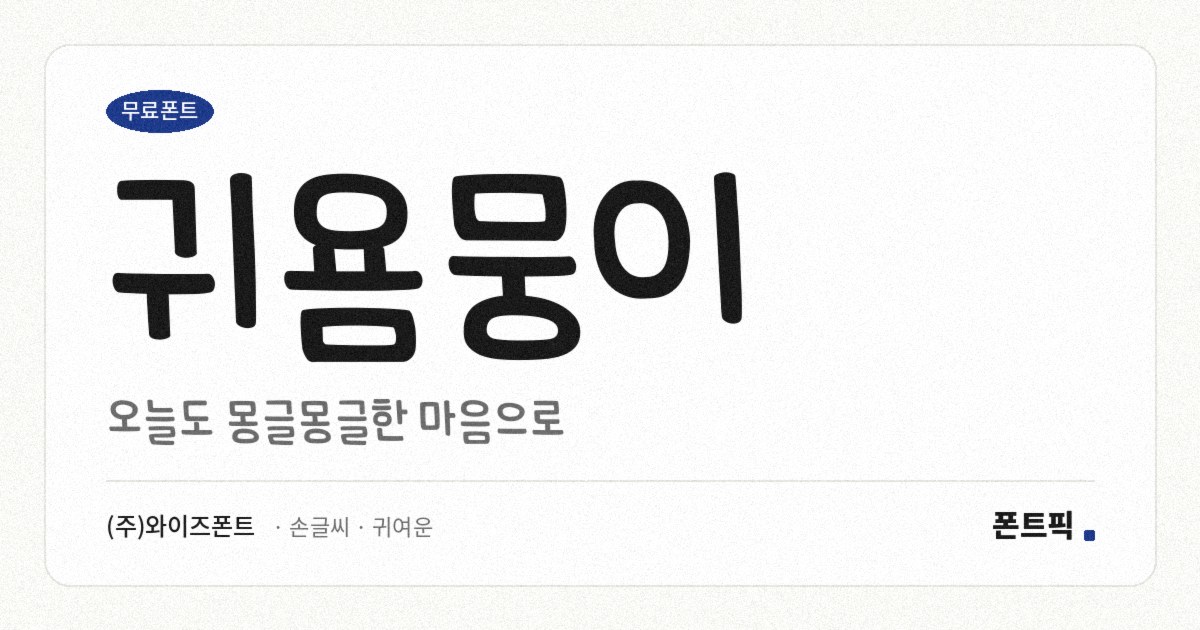
귀욤뭉이
TDTDCuteDoggy
- 분류손글씨 · 귀여운
TDTDCuteDoggy
이름처럼 둥글고 통통한 서체입니다. 획 끝을 굴리고 속을 채워 인상이 부드럽습니다.
파일에서 재어 보면 받침이 붙을 때 글자가 0.14em쯤 내려가 손글씨의 흔들림이 조금 남아 있지만, 같은 회사의 별헤는밤이나 푸들처럼 크게 오르내리지는 않습니다. 손글씨와 고딕의 중간쯤에 있는 셈입니다. 낱자는 정사각형에 가깝고 세로획이 가로획보다 3할쯤 굵습니다.
장식이 들어가지 않아 쓰임이 넓습니다. 어린이 콘텐츠나 캐릭터 굿즈, SNS 카드의 제목처럼 친근한 인상이 필요한 자리에 맞고, 획이 굵고 둥근 만큼 긴 본문에는 답답합니다. 현대 한글 11,172자를 모두 담았고 굵기는 하나입니다.